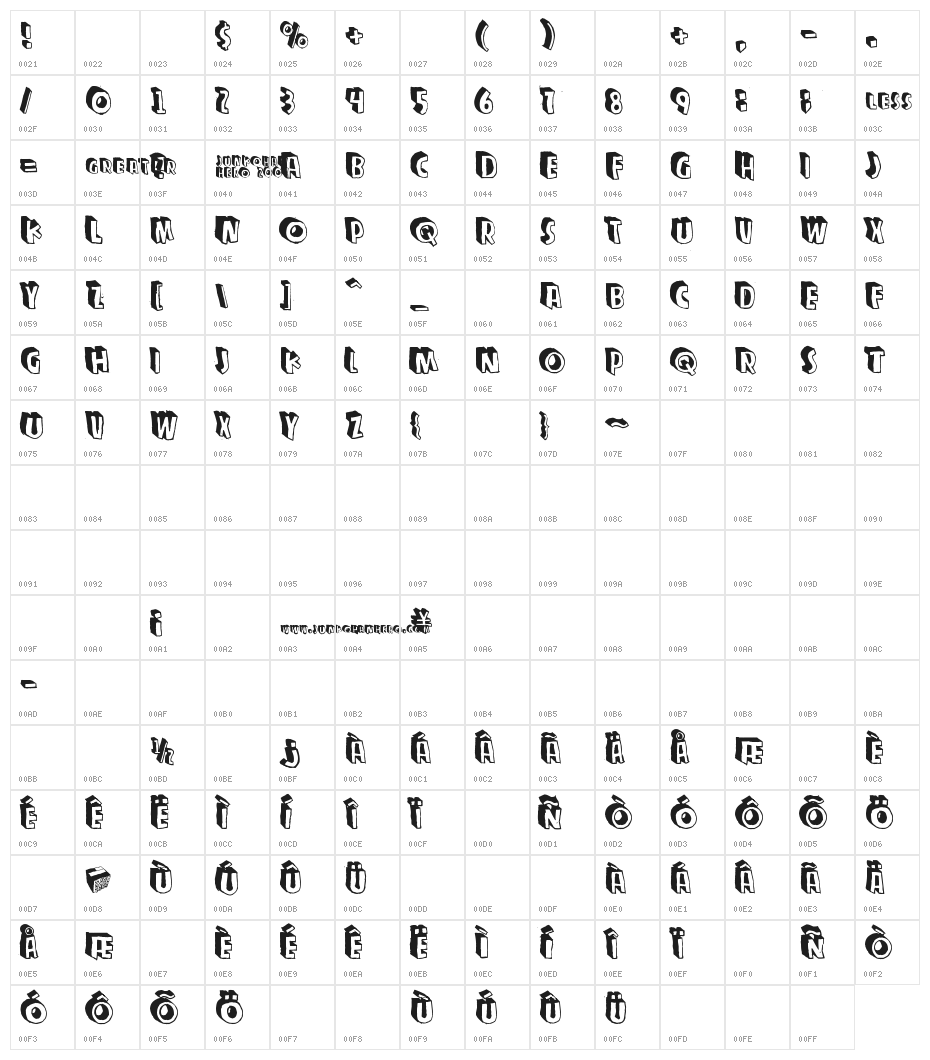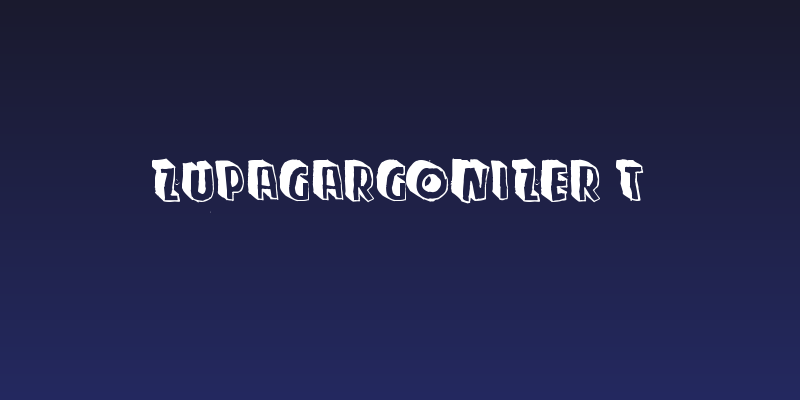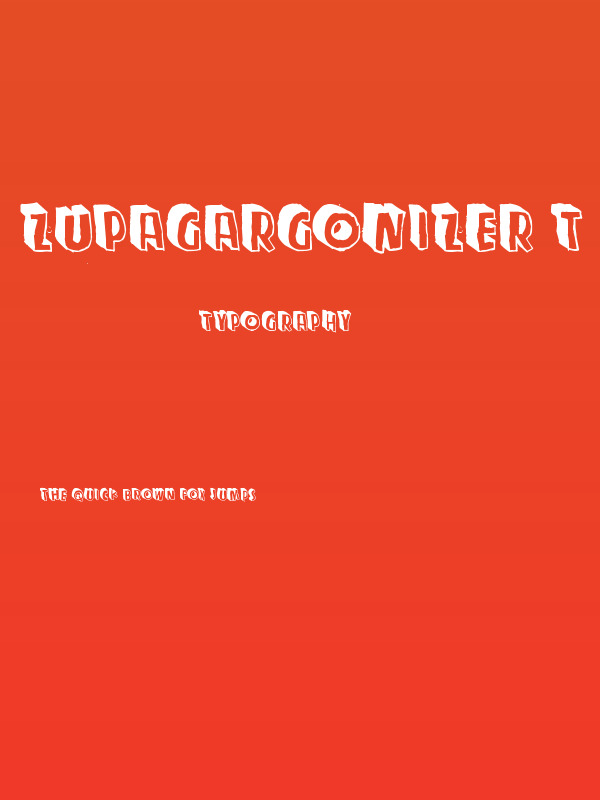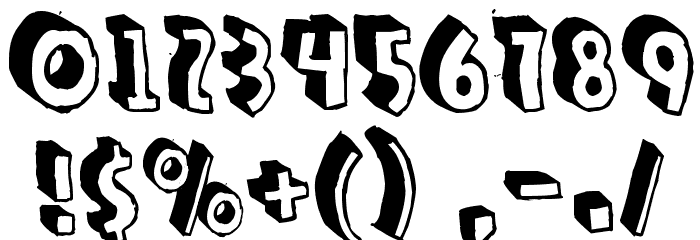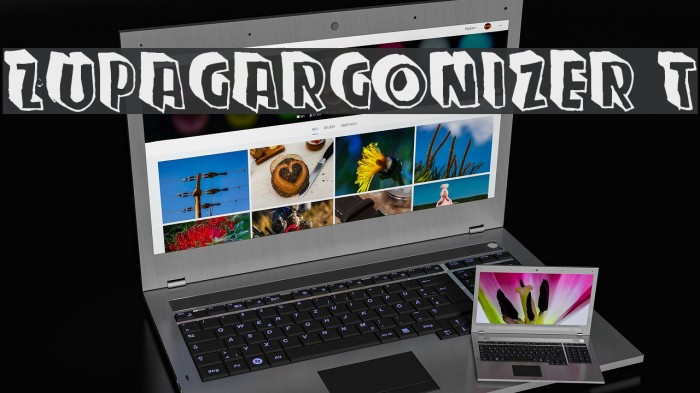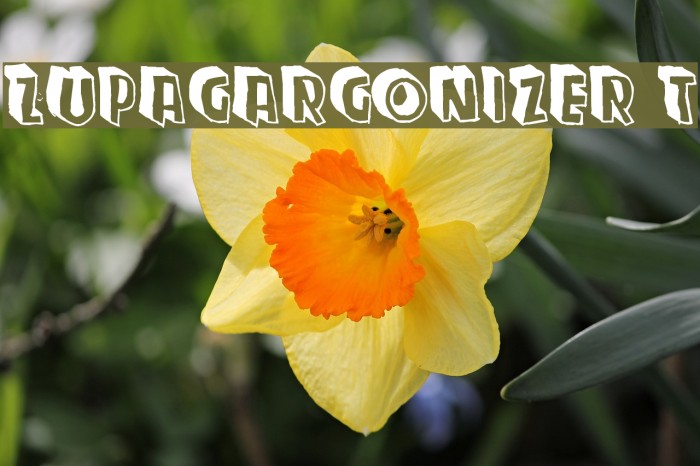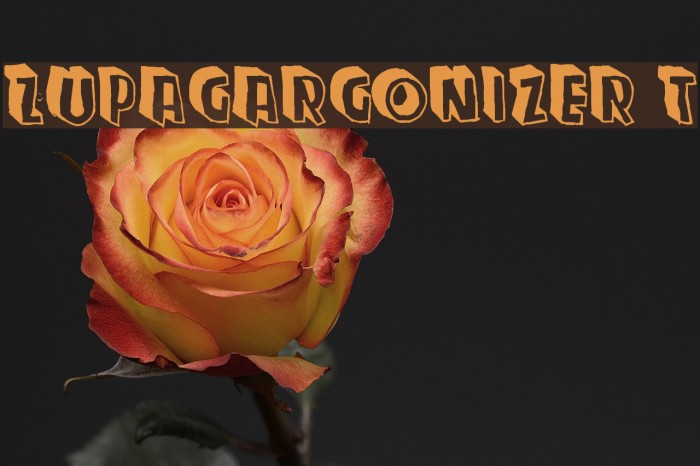
Zupagargonizer T Font
| Style général | Playful, Dynamic |
| Cas d'utilisation | Headlines, Posters, Branding |
| Projets proposés | Perfect for comic books, children's book covers, posters, and playful branding. |